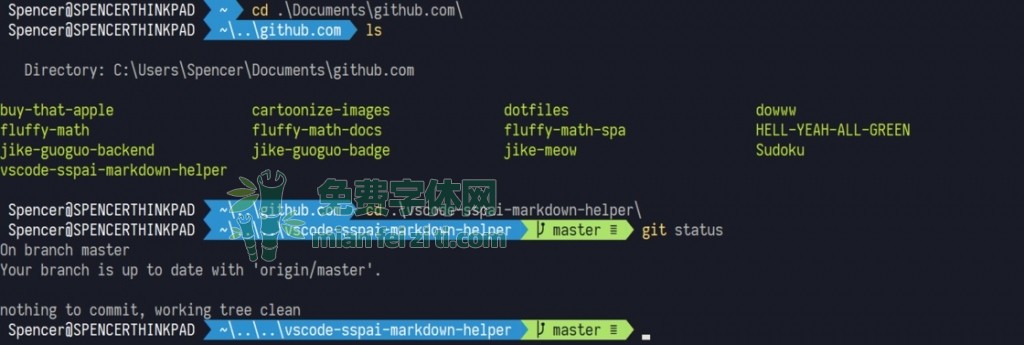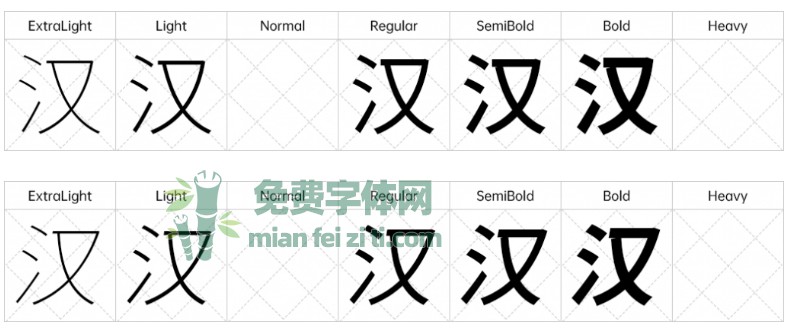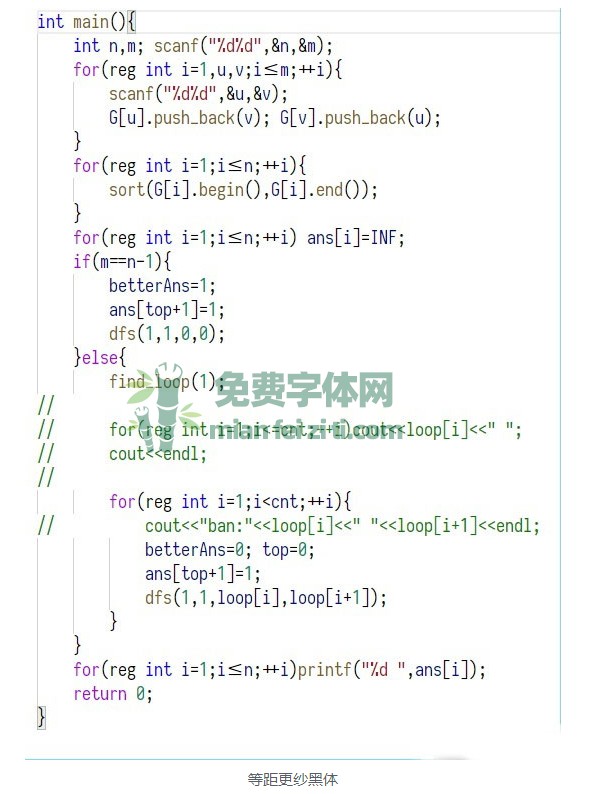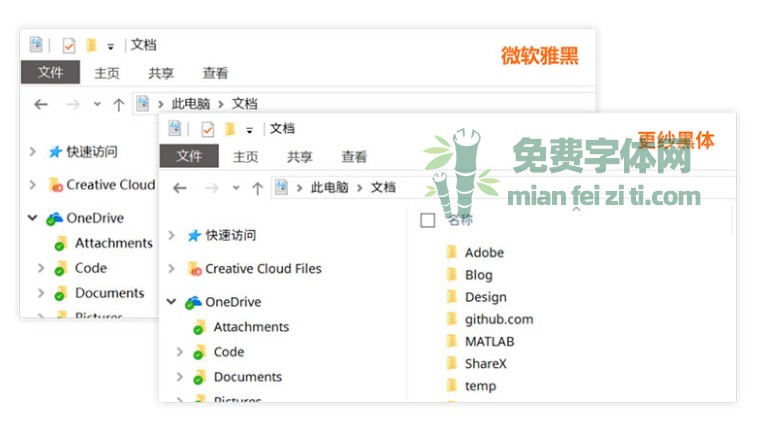
字体作者: Belleve Invis (国籍不详)字体字重:5个
更纱黑体(Sarasa Gothic),一款在100%缩放比例下有着优秀渲染效果的字体,更纱黑体由Noto Sans / Iosevka和思源黑体的汉字部分合并而来,因此简体中文基本不缺字,也有日系汉字的风格,并且是开源免费字体。
更纱黑体与思源黑体对比,主要是英文部分显示不同,英文显示更时尚。而且增加了斜体,所以免费字体网觉得用更纱黑体来代替思源黑体也未尝不可。不过思源黑体具有7字重,而更纱黑体只有5字重,这一点比思源黑体差了一点。
下图是一个更纱黑体与微软雅黑的对比,不过因为电脑是2K分辨率的屏幕,其对比并没有很明显,更多是字型上的差别,但是如果将电脑外接1080p分辨率的显示器的时候,两种字体的显示效果差别就很是明显了。总之,更纱黑体相比微软雅黑在100%缩放比例下的显示效果确实要好上一些。
更纱黑体还有一款适合代码编辑、终端的优秀等宽字体,那就是等距更纱黑体。 等距更纱黑体(sarasa-mono),由Iosevka和思源黑体组合起来的优秀等宽字体,是更纱黑体其中的一款,有着独特的“科技”风味,很适合在代码编辑、终端以及需要一些科技元素的平面设计里使用。 下图是等距更纱黑体的预览效果。
关于字体作者
更纱黑体的作者Belleve Invis是微软的软件工程师和类型设计师,致力于世界各地所有语言的文字处理和数字排版。2017年至今, 在微软公司、SDE与类型设计。他参与了下一代东亚用户界面Windows家庭的创建。创建了一个具有完全OpenType支持的基于JS的字体工具链(包括OpenTypeVariations)。改进了Office应用程序的文本布局和编辑。